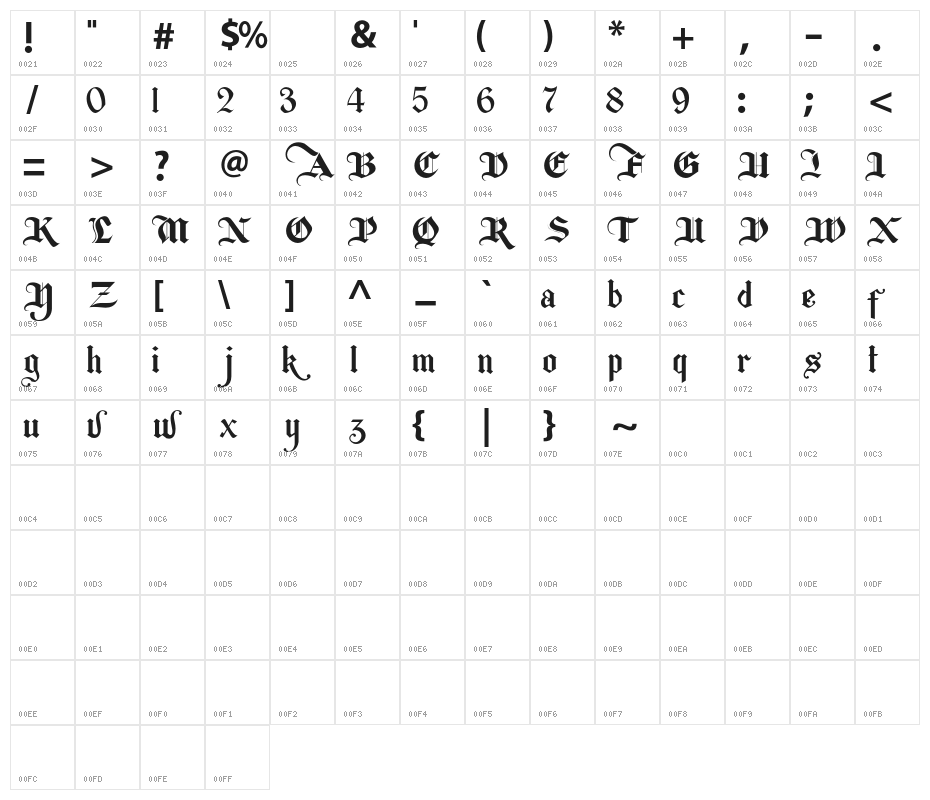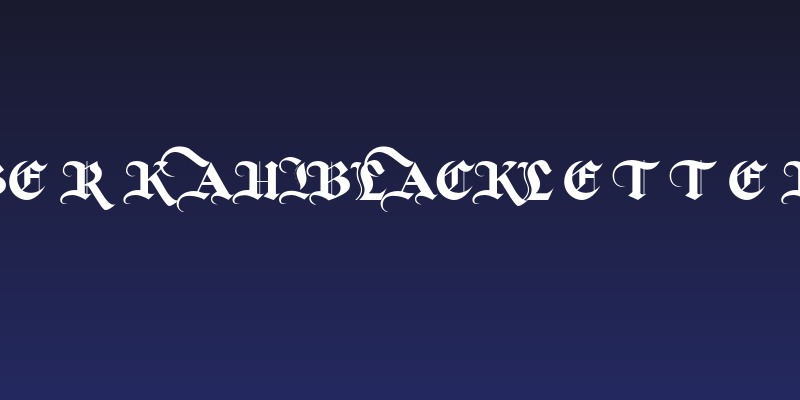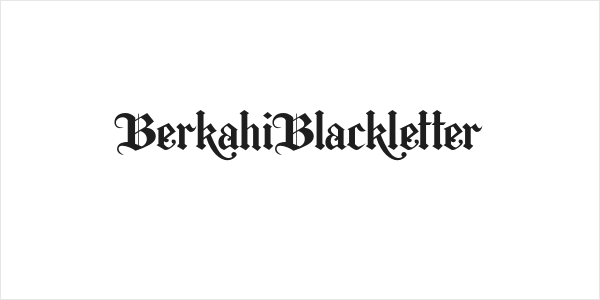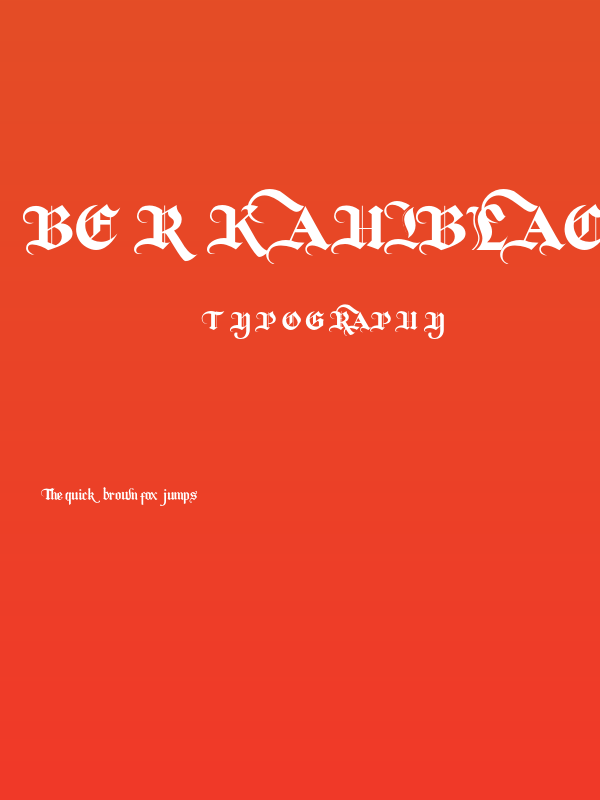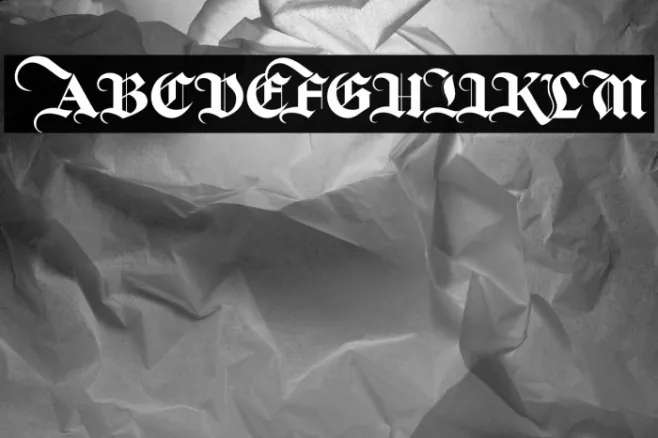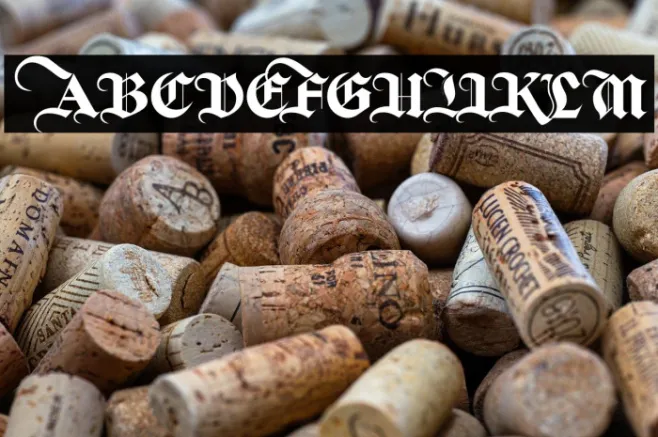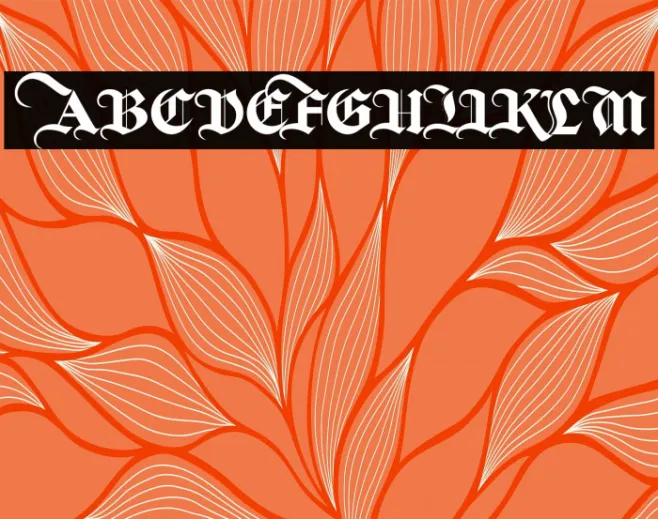
BerkahiBlackletter Font
| Famille de police | Berkahi Blackletter |
| Style | Bold |
| Catégories | Gothic |
| Cas d'utilisation | Headlines, Logos, Decorative text |
| Projets proposés | Ideal for historical documents, wedding invitations, book covers, and branding that requires a classic, sophisticated touch. |